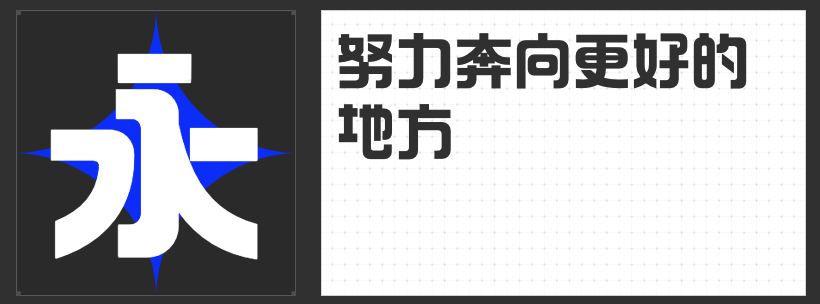
四款创意字库字体推荐:以设计语言重构视觉张力
在当代视觉传达中,字体的选择已成为品牌叙事与美学表达的核心载体。以下四款创意字库字体,以独特的结构语言与风格融合,为设计师提供突破常规的创作工具,助力作品在信息洪流中脱颖而出。
一、造字侠朝凤宋简
这款宋体以宽扁骨架构建秩序感,却在细节处暗藏矛盾美学——横画起笔的圆角与折笔的方角形成张力,撇捺曲线的流畅收笔与钩画外圆内方的几何化处理,让文字兼具力量感与柔美感。布白均匀的排版特性,使其既能驾驭传统文化场景的典雅表达,也可适配现代设计的极简风格,成为平衡历史感与未来感的视觉桥梁。
二、造字侠磅礴简繁
中正结构下,笔画以“一波三折”的运笔轨迹打破静态,粗细对比强烈的线条与飞白效果,赋予文字书写般的呼吸感。方圆转折的碰撞,既保留了传统书法的韵律,又通过现代设计手法强化视觉冲击。这款字体尤其适合需要营造历史厚重感与艺术感染力的场景,无论是文化海报还是品牌标题,皆能以动态笔意传递深层情感。
三、造字侠地铁修悦体 特粗
灵感源自地铁指路标识的手工拼贴美学,方正字形中保留了胶带切割的几何棱角与人工排版的微妙失衡。特粗字重与平直切口的组合,让文字在海报、广告标题等场景中形成强烈视觉焦点,而重心与留白的多变性则赋予排版以随机趣味。这款字体以“不完美中的个性”重新定义工业风格,成为年轻化品牌表达态度的利器。
四、造字侠热辣隶简
突破传统隶书的扁平框架,以中宫开阔的结构强化庄重感,横画对称舒展如翅膀展开,竖钩则以直线概括力量。撇捺的粗细过渡与弯钩的简洁处理,让文字在保留隶书历史底蕴的同时,注入现代设计的简洁美学。这款字体成为国潮设计、文化包装等领域传递“新古典主义”气质的理想选择。
这四款字体以不同维度诠释了创意字体的可能性——从几何美学的解构到动态笔意的捕捉,从手工温度的保留到传统基因的再造,为设计师提供了突破常规的表达语言。在追求独特视觉叙事的今天,它们将成为点亮作品的关键笔触。